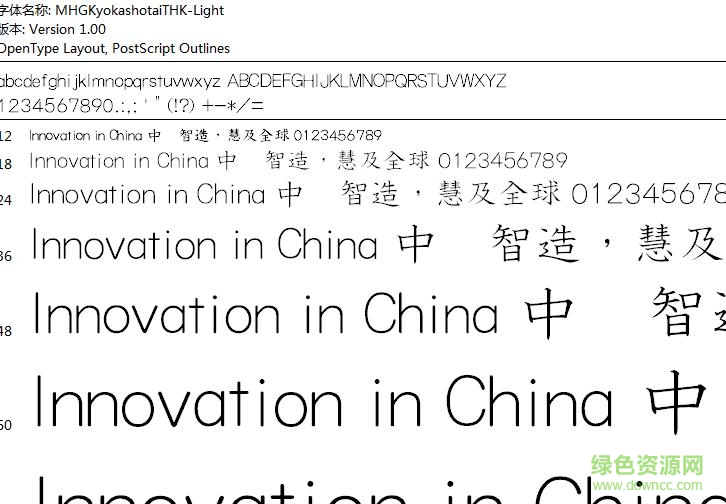
蒙納教科書體
蒙納繁和教科書體ttf是一款非常有特色的繁體字體,基于中國古代印刷字體宋體衍生而來,延續(xù)了字形端正、剛勁有力的特點(diǎn),喜歡這款字體的朋友歡迎下載使用!
蒙納繁和教科書體ttf簡介
蒙納繁和教科書體是蒙納根據(jù)日本教科書字體打造的繁體中文字體,字形清晰,棱角分明,筆挺端莊獨(dú)具美感,整體效果出眾,可適用于廣告設(shè)計(jì)、平面設(shè)計(jì)、印刷包裝等領(lǐng)域!